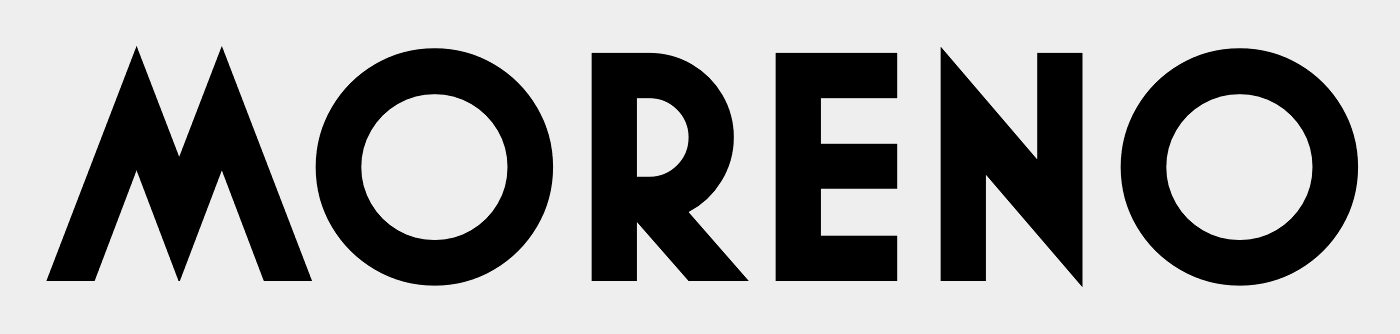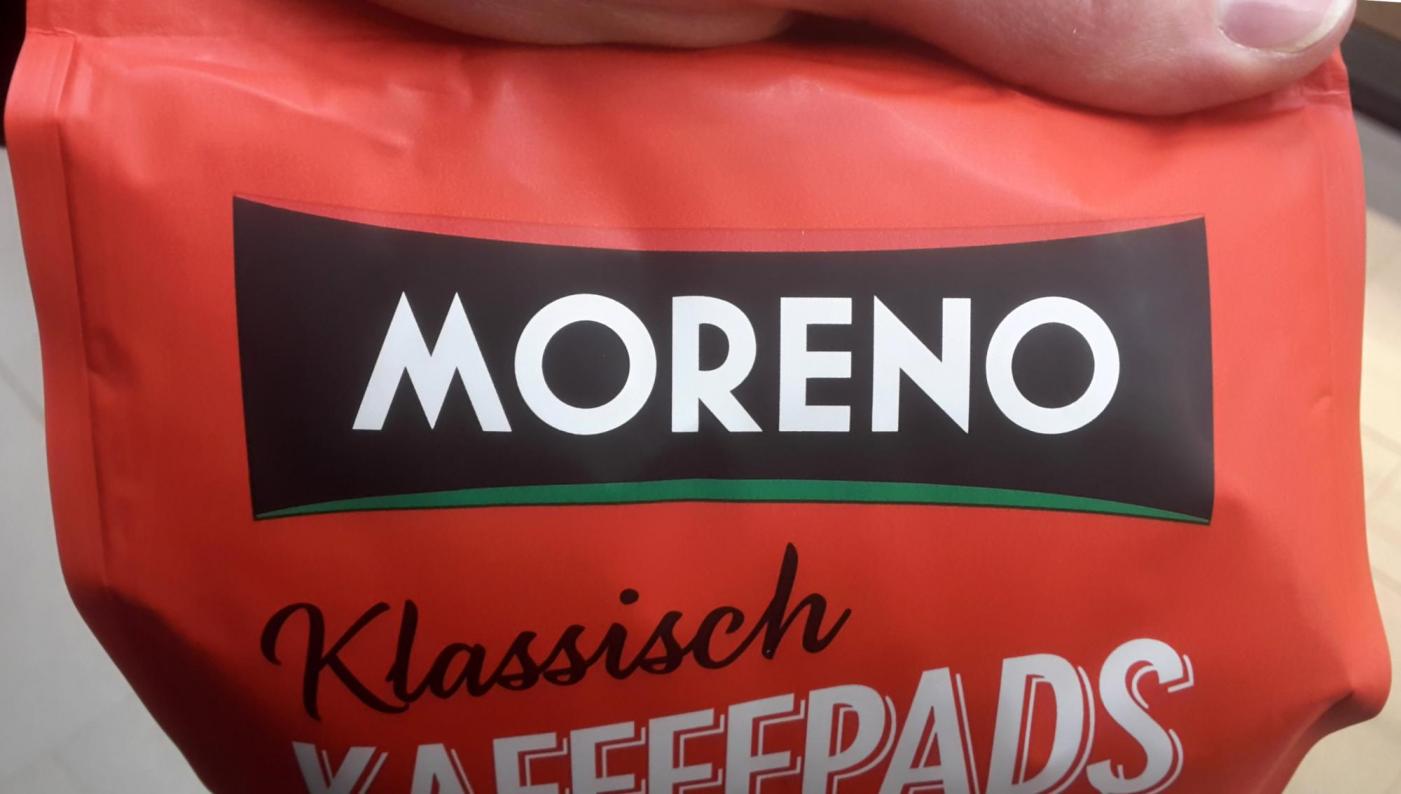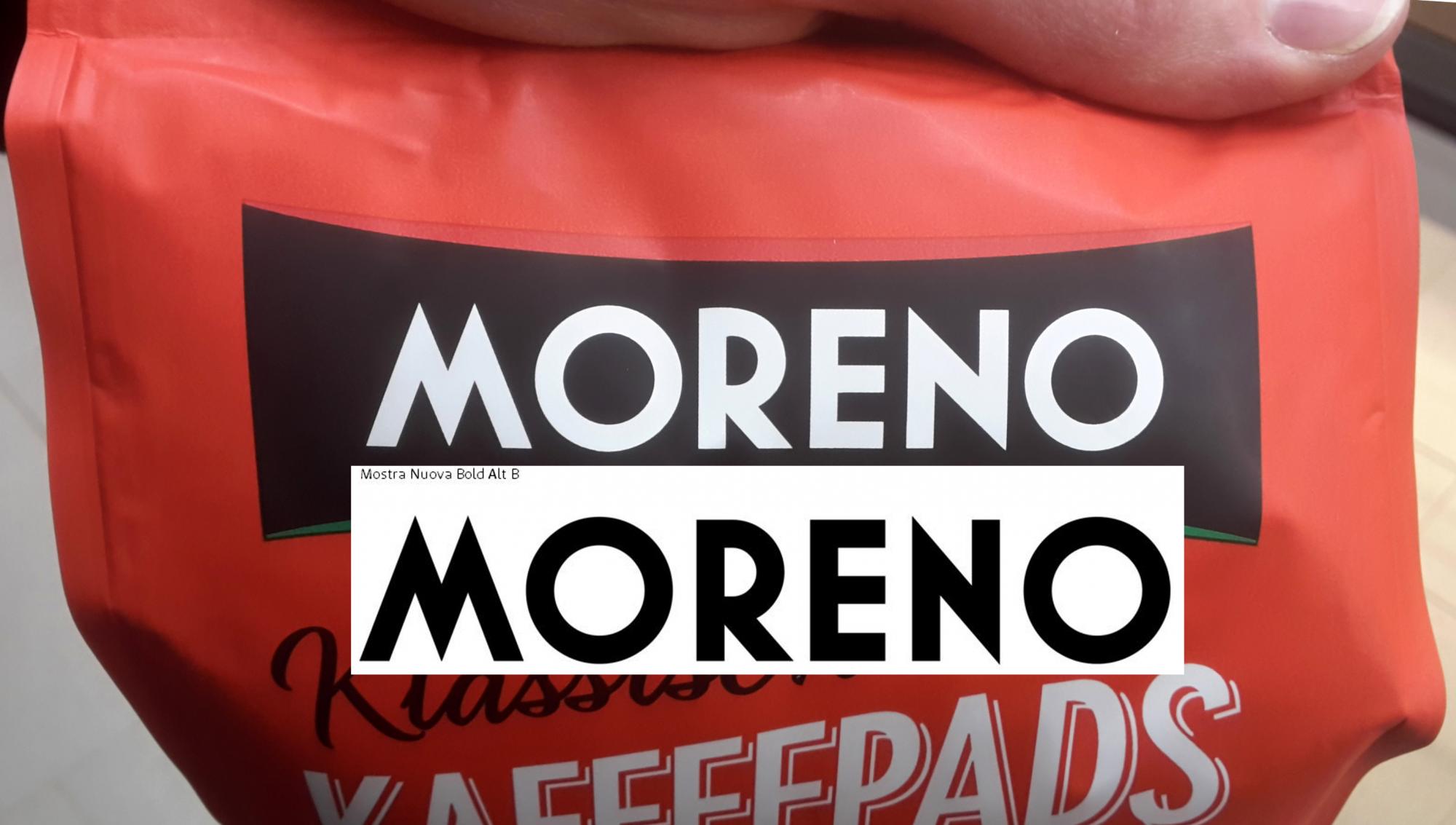
Serifenlose Groteske auf Verpackung (ALDI/Moreno)
Könnte der Mostra entspringen mit einem nachgearbeiteten N, das nun leider eine zu breite Diagonale aufweist.
Mit dem "N" bin ich unsicher. Es ist schmaler.
Wie Bertel bereits schrieb scheint das N nachbearbeitet zu sein.